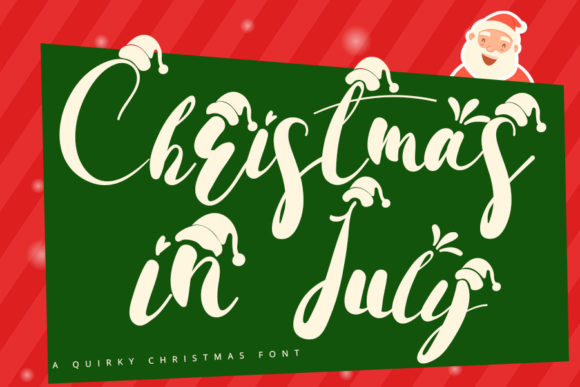
[Creativefabrica] Christmas in July Font (2021)
Christmas in July - ослепительный шрифт. Этот шрифт аккуратно выполнен и отличается высокой детализацией.